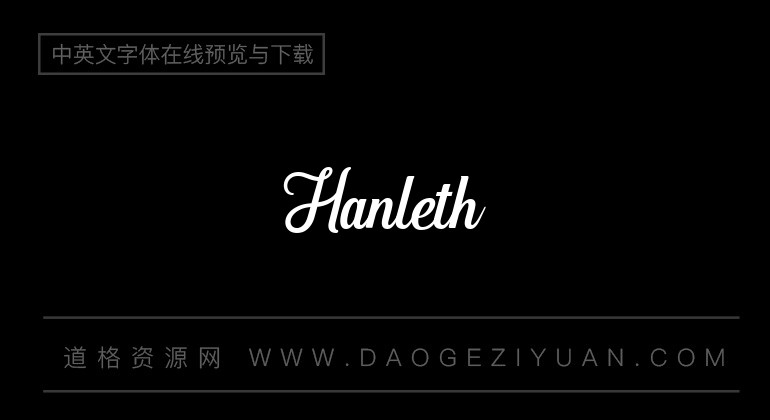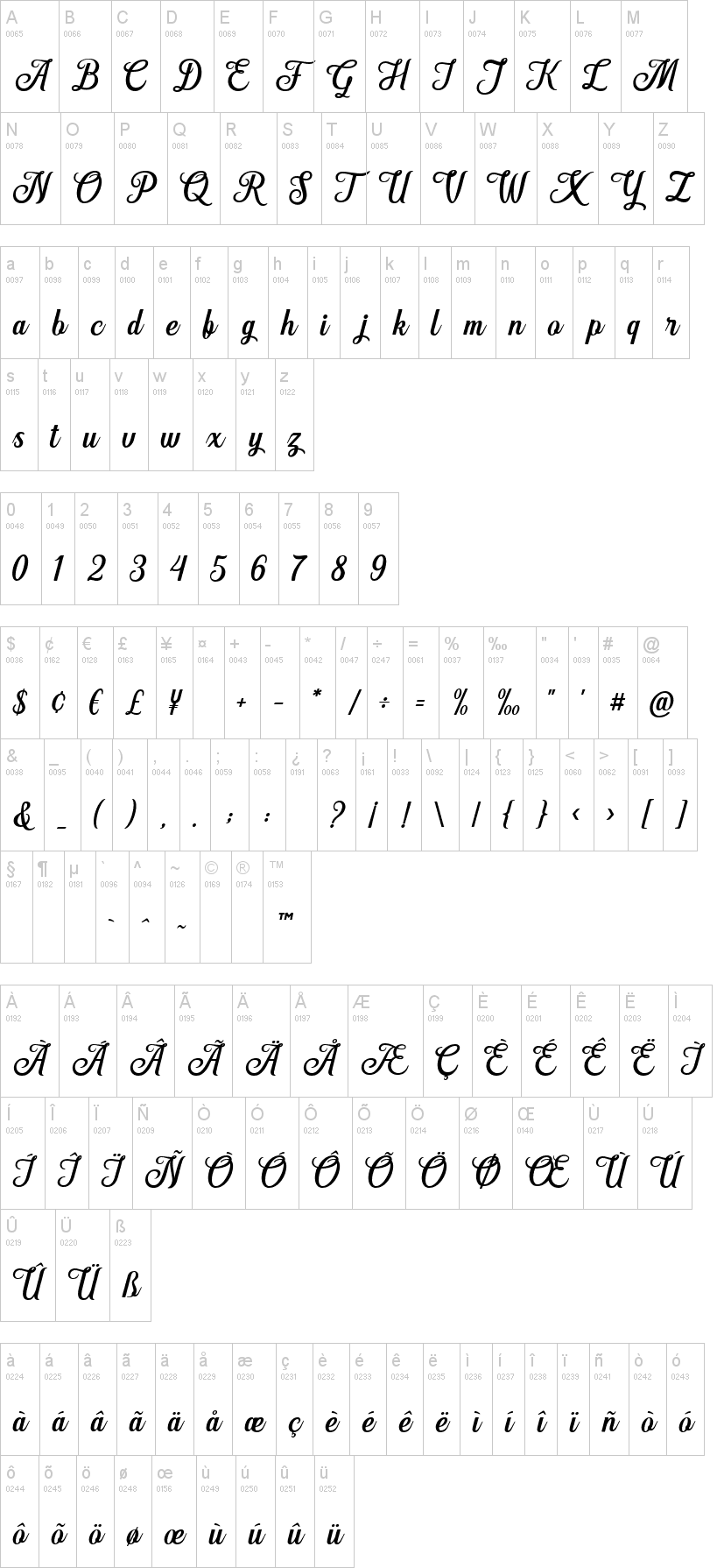
Hanleth 字体是一款由英国设计师Chloe Meineck设计的新英文字体,它拥有轻快、清新、活泼的风格,适用于广告、品牌、展示及其他各种文案应用场景。Hanleth字体在每个字母之间有足够的空间,使文字更加简洁,而且每个字母都有明显的视觉特征,使文字更加活泼有趣。同时,Hanleth字体还具有英语发音的特点,使得文字更具有可读性。内容介绍
Hanleth是一款非常不错的手写艺术字体,具有很好的视觉感,适合于文化类的宣传设计、商业类品牌的广告和产品包装设计以及个性化文字排版等较多场景。